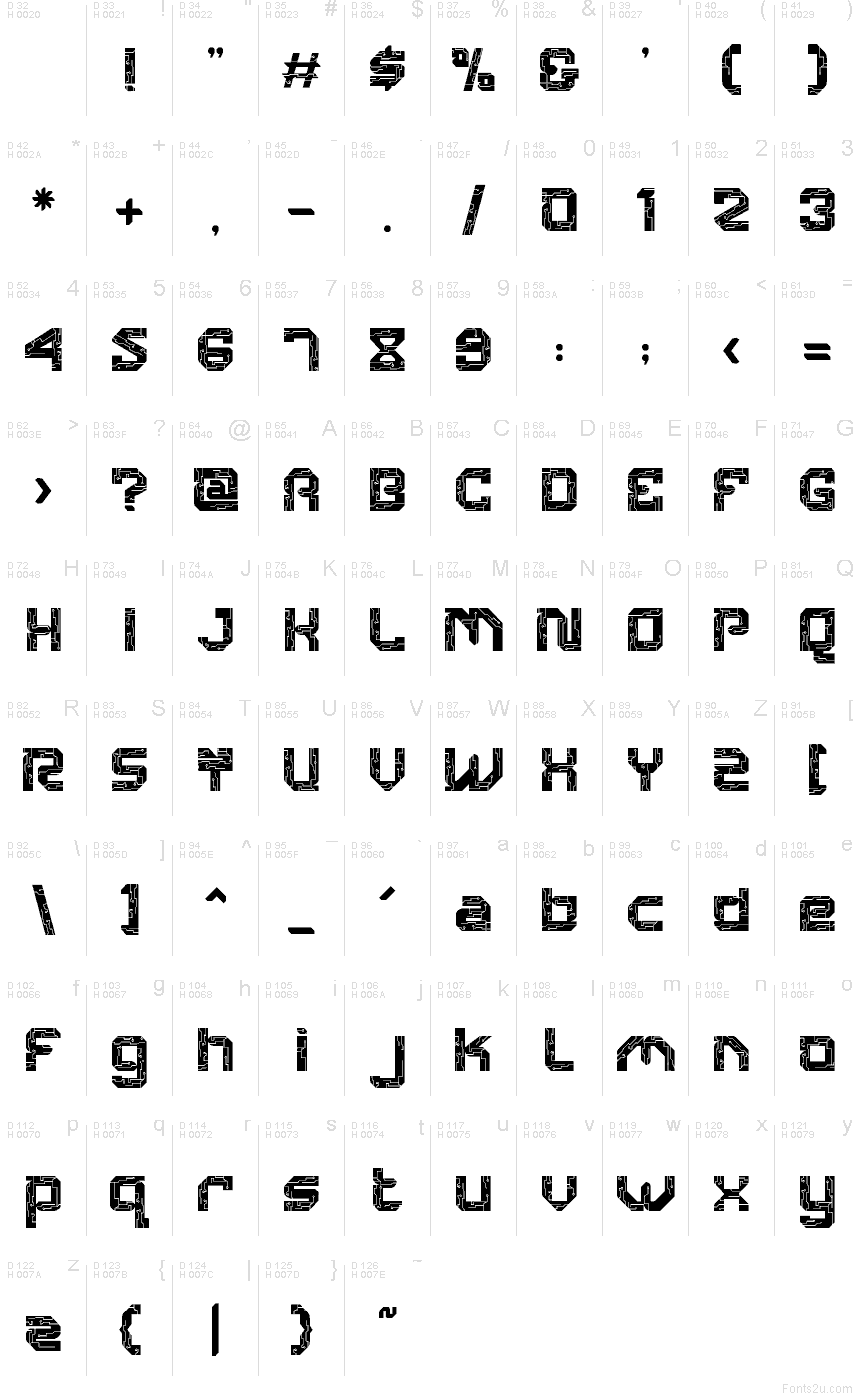
Cyber Crown One od Putracetol Studio je bezplatné bezpatkové písmo typu display inspirované deskami plošných spojů. Každý znak se mění v bludiště cest, uzlů a hranatých kanálků. Tento opakující se motiv PCB dodává designu autentický technický vzhled namísto generického futurismu a díky robustním siluetám zůstávají obvody čitelné v celé sadě znaků.
Nejlépe se hodí pro herní tituly, sci-fi plakáty, grafiku technologických akcí, streamery nebo promo materiály aplikací, kde elektronické detaily skvěle podtrhnou téma. Vynikne také u krátkých log a obalů alb, zejména pokud hledáte písmo, které vypadá jako vyleptané do hardwaru, nikoliv jen jako prostý geometrický tvar.